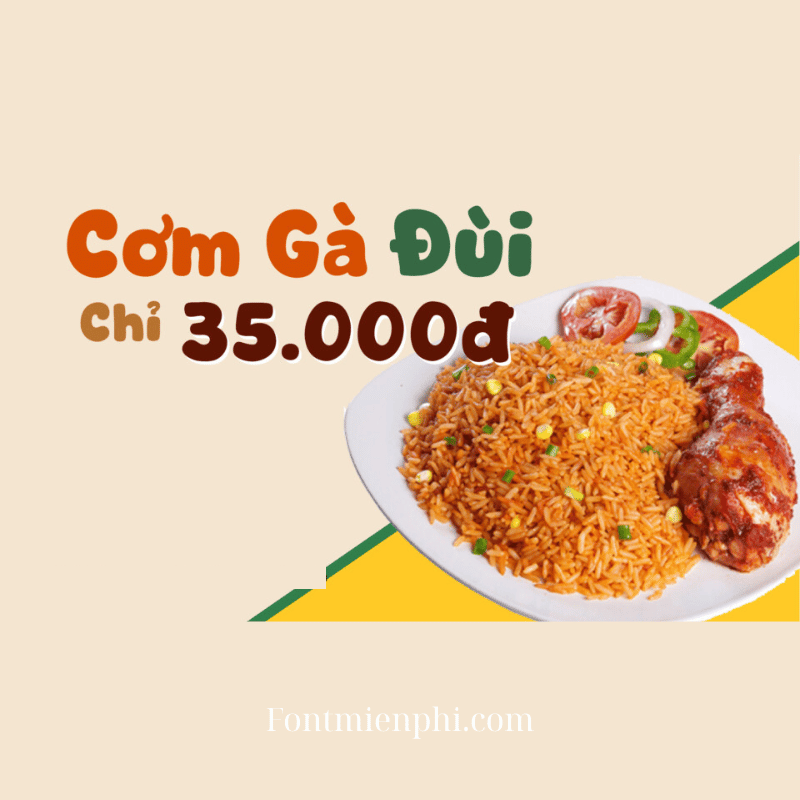
Font Việt hóa 1FTV VIP Cute Dino
Font Việt Hóa 1FTV VIP Cute Dino – Nét Chữ Đáng Yêu, Sáng Tạo Không Giới Hạn
Giới thiệu:
Font Việt hóa 1FTV VIP Cute Dino là bộ font chữ độc đáo, dễ thương với phong cách hình chú khủng long ngộ nghĩnh. Được thiết kế tinh tế, font chữ này hỗ trợ đầy đủ tiếng Việt, phù hợp cho thiết kế đồ họa, bài viết, in ấn và nhiều dự án sáng tạo khác. Với nét chữ mềm mại, đáng yêu, 1FTV VIP Cute Dino sẽ là lựa chọn hoàn hảo để tạo điểm nhấn ấn tượng.
Đặc điểm nổi bật:
✔ Hỗ trợ tiếng Việt đầy đủ – Tương thích với mọi văn bản tiếng Việt, không lo lỗi font.
✔ Phong cách dễ thương – Nét chữ kết hợp hình khủng long ngộ nghĩnh, phù hợp thiết kế trẻ em, quà tặng, poster.
Kết luận:
Font Việt hóa 1FTV VIP Cute Dino mang đến phong cách độc đáo, giúp sản phẩm thiết kế của bạn trở nên sinh động và thu hút. Hãy tải ngay để khám phá những ý tưởng sáng tạo không giới hạn!